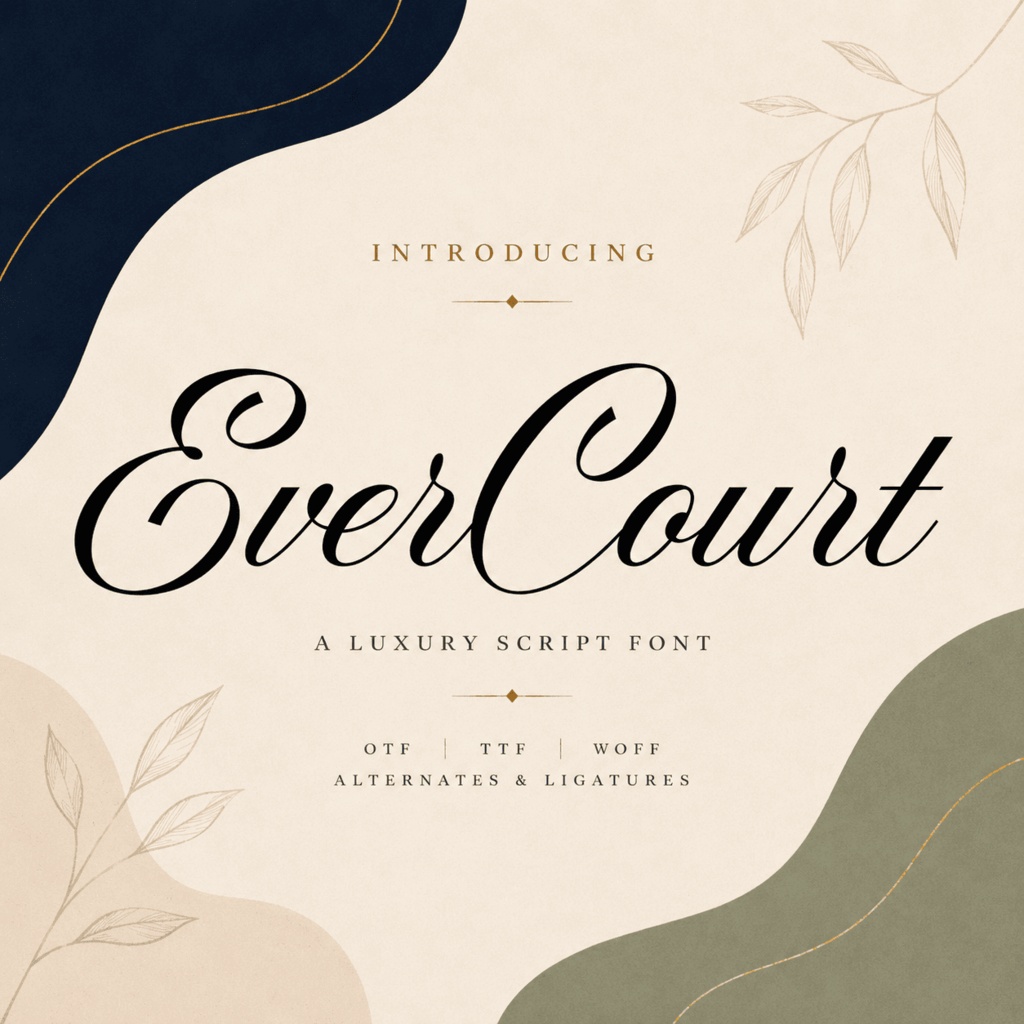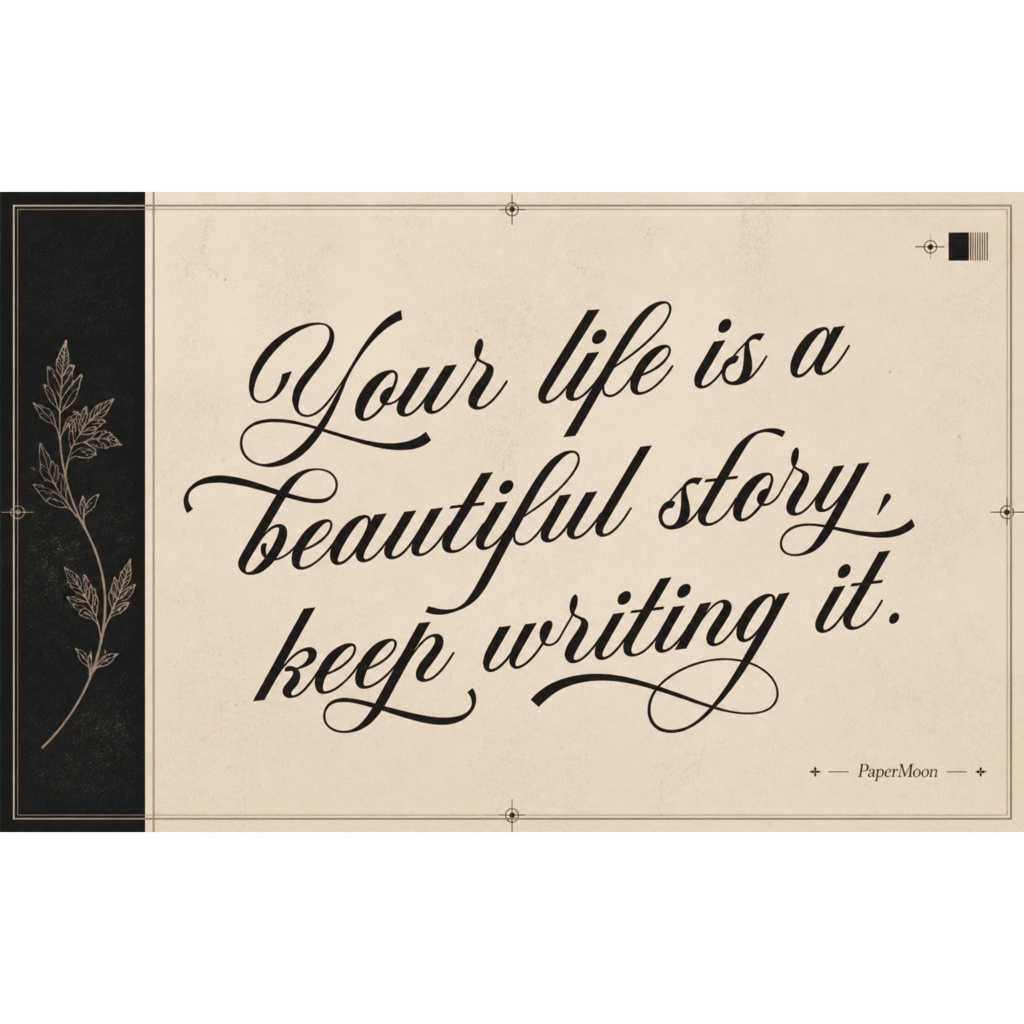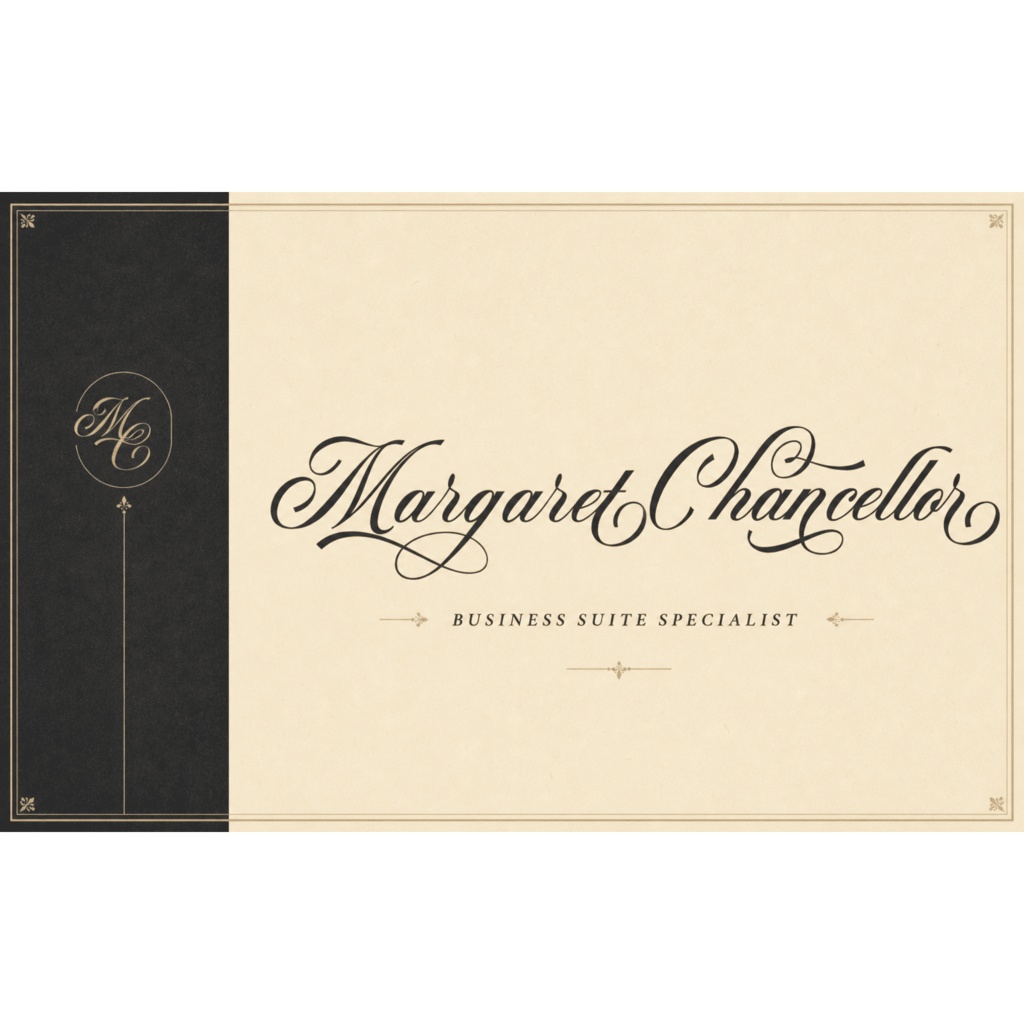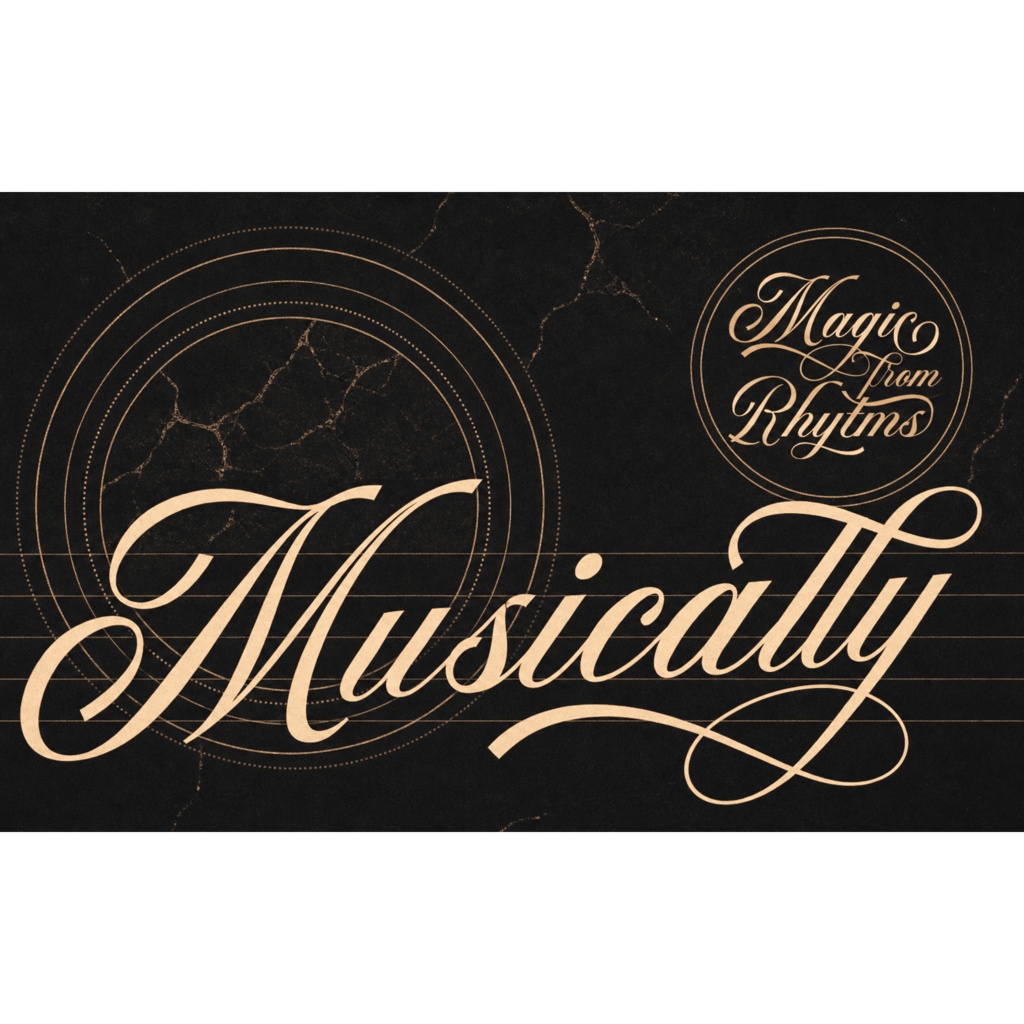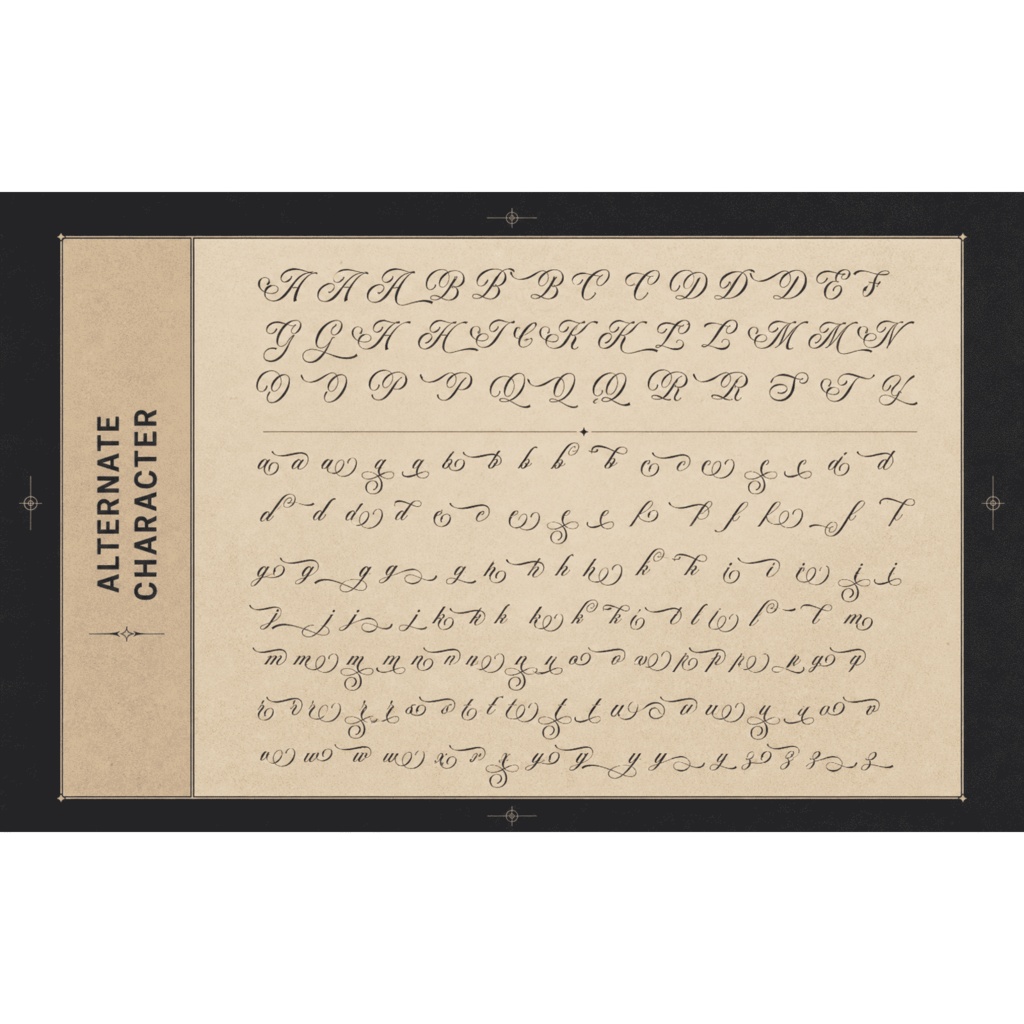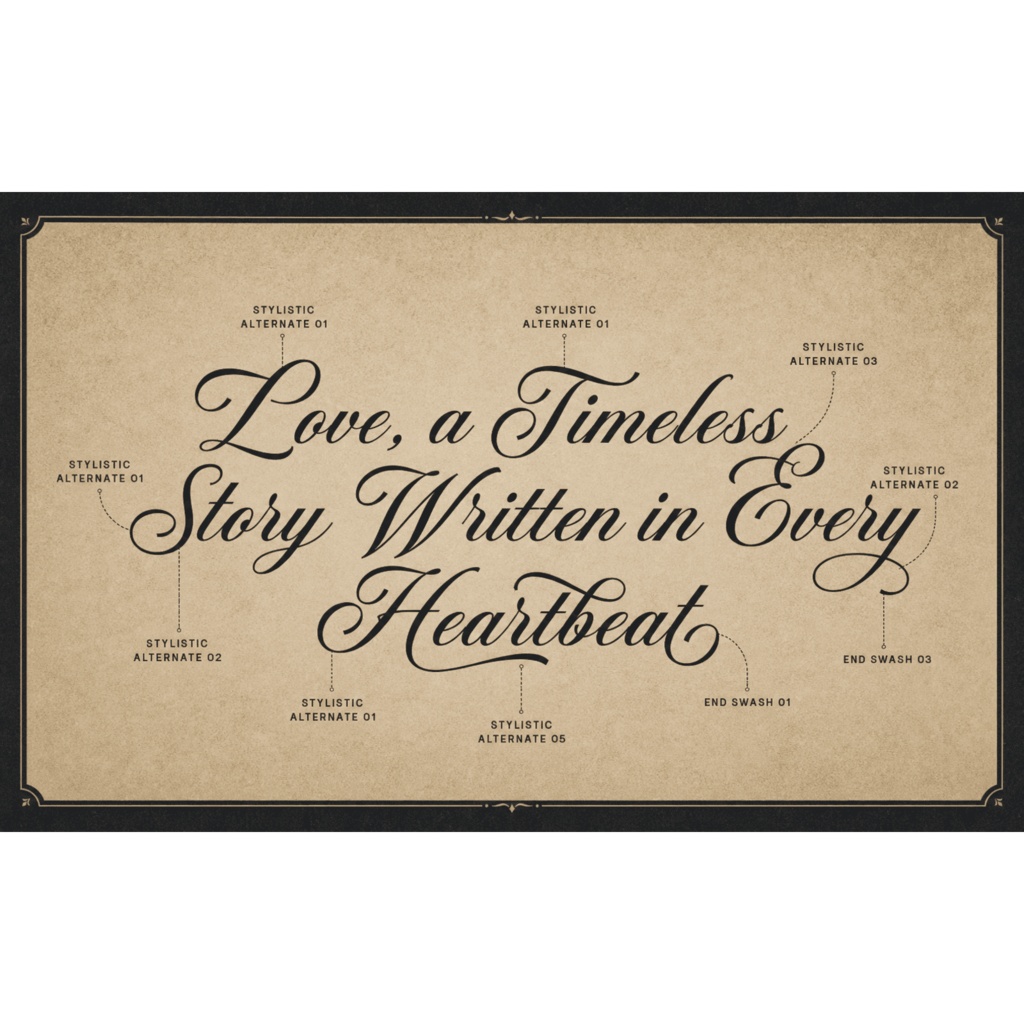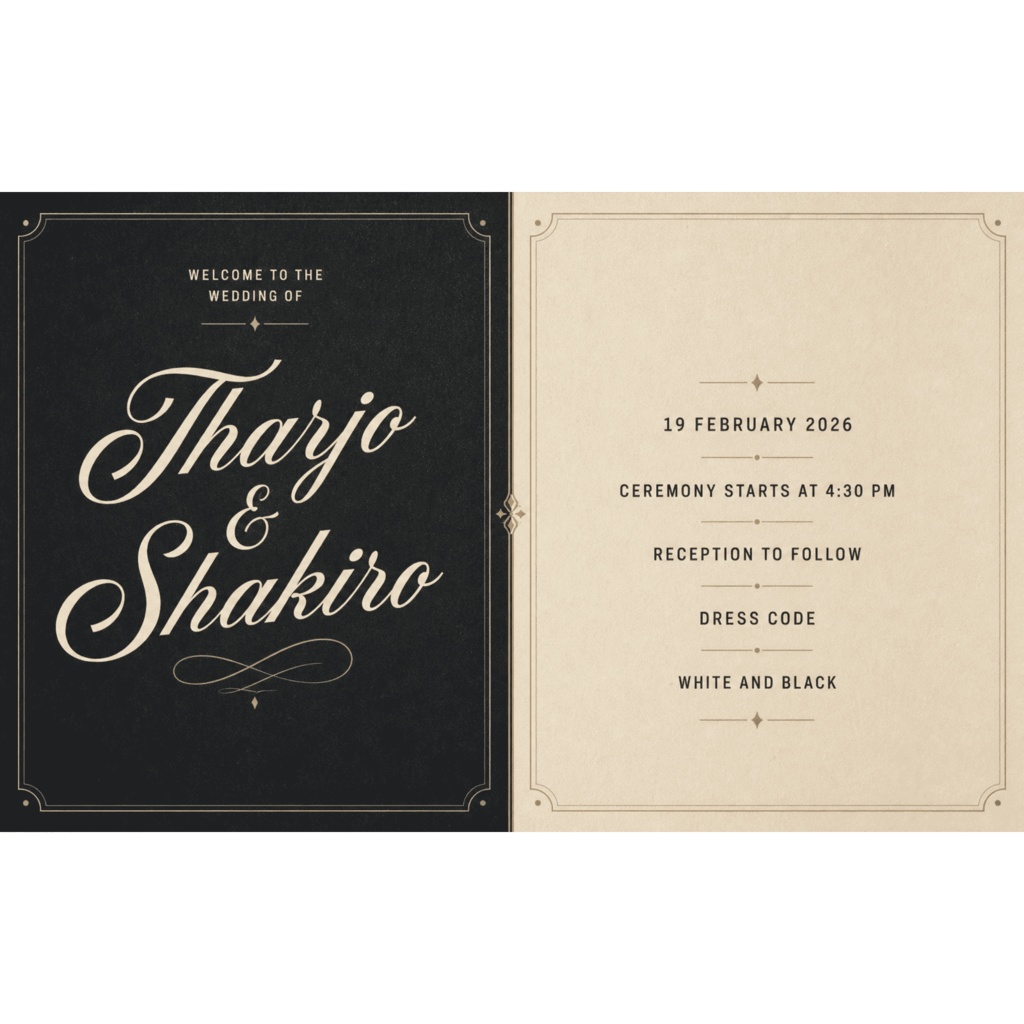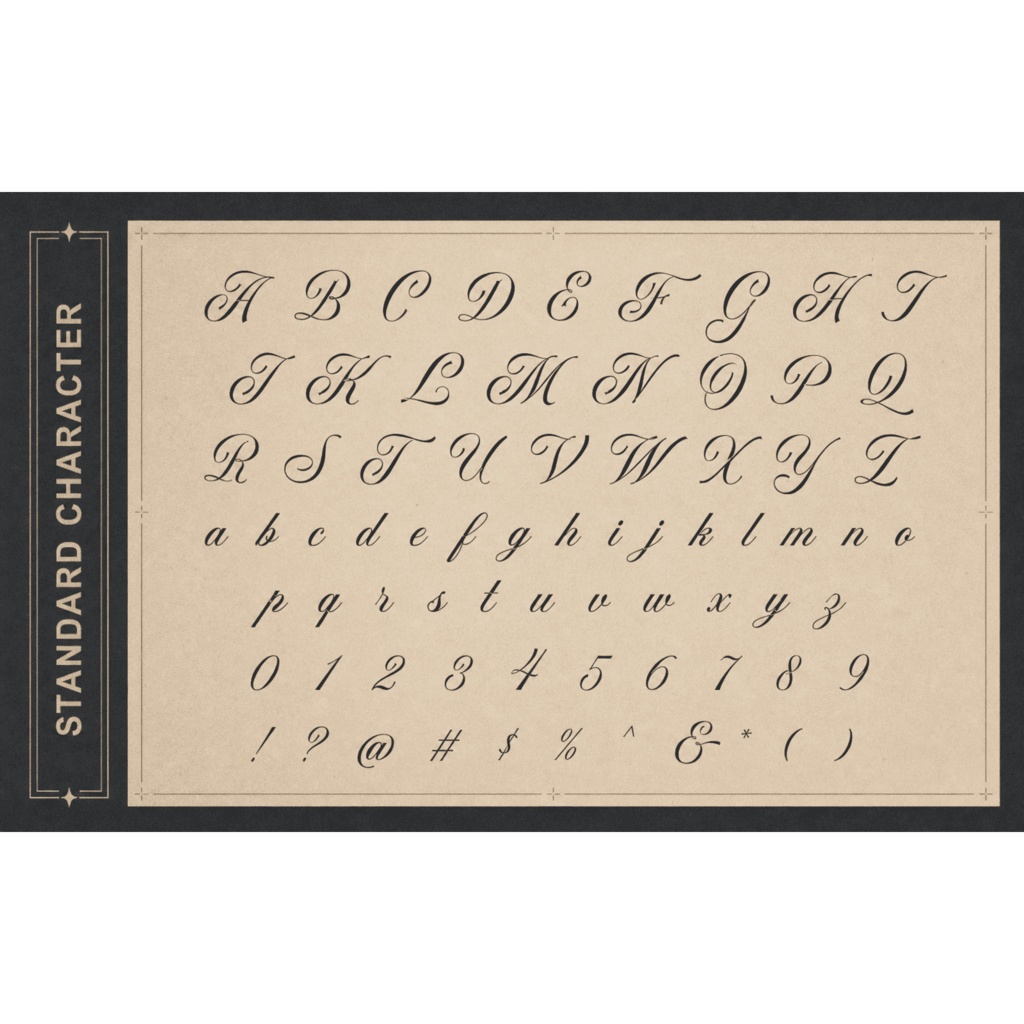
Evercourt | ロマンティックな筆記体フォント | ウェディング・ロゴ向け Script Font
Evercourt(エバーコート)は、ウェディング・ステーショナリー、ロゴ、エディトリアルデザインのためのロマンティックな筆記体(Script)フォントです。流れるように繋がる小文字と、表情豊かな大文字・飾り文字のオルタネートを備え、招待状の一文字から小さなモノグラムまで、思いを込めた言葉を美しく見せます。 単一の Regular ウェイトに全機能を収めた、完成度の高い欧文フォントです。OpenType のスタイリスティックセット(ss01–ss06 / salt)で飾り文字をワンクリックで切り替えられるので、レイアウトごとに違う表情を作れます。筆記体らしい温かみと、グラフィックにも負けない整った字面を併せ持っています。 収録内容 / Included - 1 style(Regular)— Evercourt-Regular:4形式(OTF / TTF / WOFF / WOFF2) - 363グリフ(OTF/WOFF/WOFF2。TTF版はビルド差により364グリフ) - OpenType:GSUB スタイリスティックオルタネート(salt, ss01–ss06)、GPOS カーニング(kern) - fsType = 0(インストール可能埋め込み) 対応文字 / Character Set - 基本ラテン(大文字 A–Z、小文字 a–z、数字 0–9、句読点・記号)に加え、西ヨーロッパ諸語のアクセント文字(Latin-1 ベース)に対応 - 日本語(かな・漢字)、Cyrillic、Greek は収録されていません。欧文専用フォントです。 - 語尾の飾り(エンドスウォッシュ風)フォルムは独立した swsh 機能ではなく、スタイリスティックセット(ss01–ss06 / salt)から選択します。liga 合字機能は含まれません。 用途 / Uses - ウェディング招待状・セーブザデート・挙式プログラムなどのウェディングステーショナリー - ロゴ・モノグラム、ブティックやフローリスト、ライフスタイルブランドのブランディング - グリーティングカード、エディトリアルの引用見出し、パッケージのアクセント、ラブレター風のSNS・サムネイル文字 - 同人誌・グッズ・配信サムネイルのタイトル文字など 形式 / Formats - Evercourt-Regular.otf / .ttf(印刷・デザイン用途) - Evercourt-Regular.woff / .woff2(Web は @font-face で利用) 対応環境 / Compatibility - Adobe Photoshop / Illustrator / InDesign、Affinity、Figma、Canva、Procreate、Cricut Design Space、Silhouette Studio ほか、OTF/TTF を読み込めるアプリ全般 - Web プロジェクトは WOFF/WOFF2 に対応 利用許諾 / License - 本商品のライセンス条件は現在確認中です。商用利用を約束するものではありません。 - フォントファイル自体の再販・再配布・埋め込みは制限されます。商用利用の前に、書面によるライセンスをご確認ください。 - Copyright (c) 2026 PaperMoon. All Rights Reserved. 更新 / Notes - フォント名・メタデータは準備済みProパッケージより確認済み(Evercourt / Regular、vendor PMON)。デモ・フリーミアム・無料サンプル商品は含まれません。本商品は有料Proパッケージのみです。